Румынские Ș, Ț и знаки под буквами: как проверить шрифт и текст
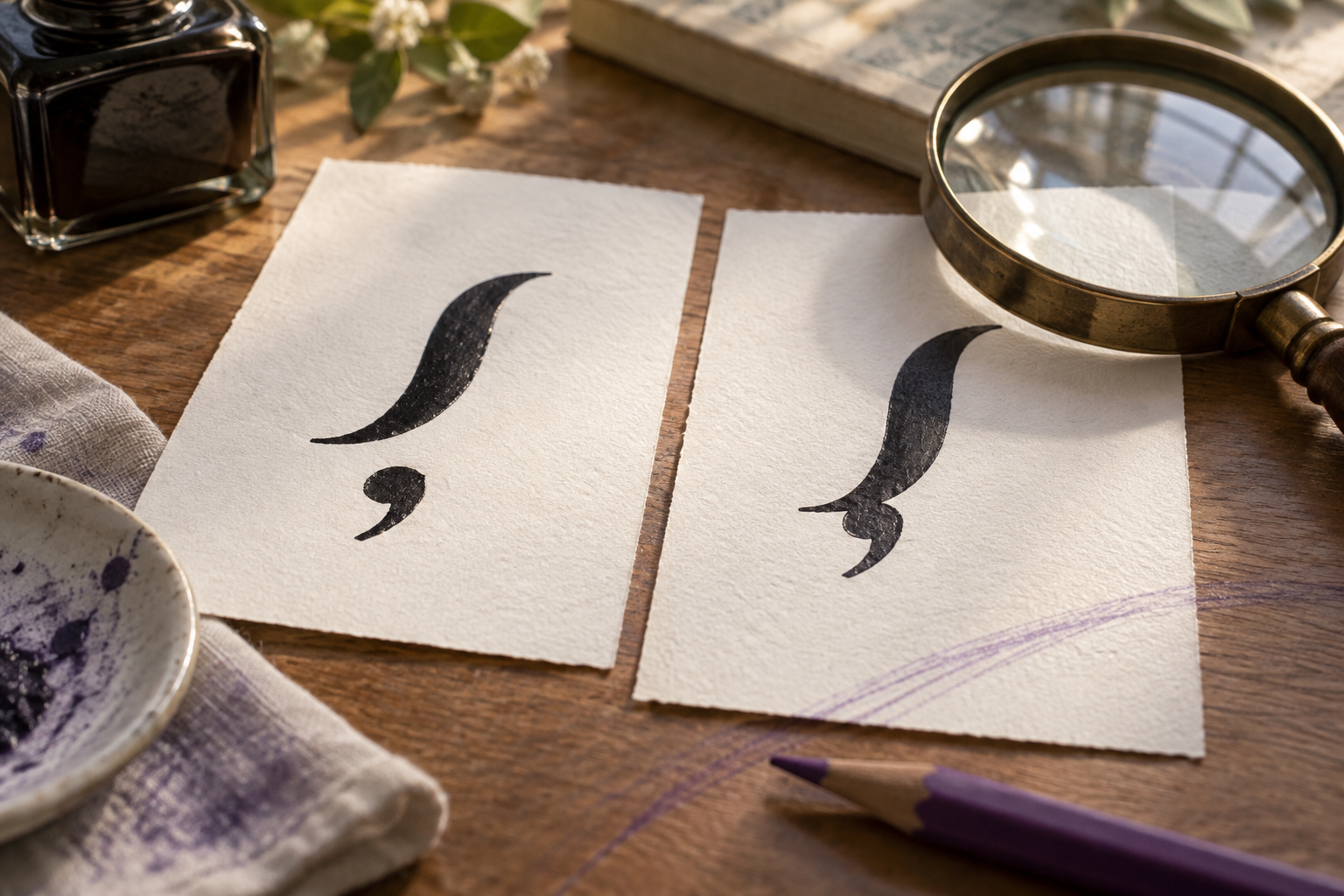
В румынском тексте буквы Ș/ș и Ț/ț несут собственные звуки и должны оставаться различимыми во всём наборе: в строчных и прописных формах, после копирования, при экспорте и на странице. Главная ловушка — похожие буквы с седилью: в старых данных они могли обозначать румынскую запятую снизу, хотя в Unicode у них отдельные коды и назначения. Проверяйте не только рисунок, но и сам текст.
Почему румынские знаки снизу легко перепутать
В румынском используются четыре буквы с запятой под основой: Ș, ș, Ț и ț. Их внешняя деталь располагается снизу, но это не просто декоративная вариация седили. Например, румынская строчная ș с запятой снизу отличается и от турецкой ş с седилью, и от обычной s. В наборе эти различия отвечают за правильное написание слов, поэтому шрифт должен показывать запятую явно, а текст — содержать подходящие символы.
Сходство кодов создаёт практическую проблему. В Unicode для румынских букв с запятой снизу предусмотрены U+0218 Ș, U+0219 ș, U+021A Ț и U+021B ț. У букв с седилью другие кодовые точки: U+015E Ş, U+015F ş, U+0162 Ţ и U+0163 ţ. В документации Unicode отдельно описана путаница, возникшая в старых наборах символов: один знак исторически использовали для нескольких визуально похожих форм. Для нового румынского текста следует различать запятую снизу и седиль, а при разборе старых данных учитывать возможную неоднозначность (Unicode Core Specification, раздел о запятой и седиле).
Начните с того, какие данные должен поддерживать шрифт
До рисования или проверки составьте короткий список ожидаемых текстов. Для обычных румынских фраз включите слова с ș и ț, заглавные буквы в заголовках или именах, а также прописные версии Ș и Ț. Если шрифт будет применяться вместе с турецким или в старых архивах, добавьте отдельно Ş/ş и Ţ/ţ. Это поможет не принять одну форму за другую и понять, где нужна языковая поддержка, а где — совместимость с полученными данными.
Полезно разделить задачу на три уровня:
- Символ есть в файле. Для каждого знака назначена отдельная кодовая точка и глиф; наборщик не подменяет его пустым прямоугольником или символом из другой гарнитуры.
- Форма соответствует языку. У румынских букв видна запятая снизу, а у символов с седилью — характерная форма седили. В маленьком размере отметка не должна сливаться с основой.
- Текст переживает рабочий маршрут. Символ не меняется при вставке, сохранении, экспорте макета, загрузке на сайт или повторном открытии файла.
Эти проверки отвечают на разные вопросы. Один красивый пример слова не доказывает, что в шрифте есть все четыре прописные и строчные формы. А наличие кодовой точки не гарантирует, что глиф хорошо нарисован, правильно привязан к метрикам и останется читаемым в конкретном кегле.
Составьте тестовый набор без случайных подмен
Возьмите по одному короткому слову или сочетанию для каждой нужной буквы. В тесте должны отдельно встречаться Ș, ș, Ț и ț, а рядом — обычные S/s и T/t. Если проверяется соседство с турецким, добавьте Ş/ş и Ţ/ţ. Не ограничивайтесь демонстрационной строкой ȘșȚț: она показывает наличие знаков, но почти ничего не говорит о ритме слова, интервалах или заметности нижних отметок.
Для проверки соседства удобно использовать три типа фрагментов: короткое слово с одной целевой буквой, слово с несколькими знаками и смешанный фрагмент, где рядом стоят S/T и румынские буквы. Сравните строчные и прописные версии в одной строке, затем повторите сравнение на более мелком кегле. Внизу отметки легко теряются у тесной строки или попадают в межстрочный интервал — это видно в контексте лучше, чем в таблице глифов.
Добавьте к образцу контрастную пару, например румынскую ș рядом с турецкой ş. Увеличьте фрагмент настолько, чтобы различить характер нижнего знака, а затем уменьшите до размера реального макета. Если две формы почти одинаковы, проверьте, не использует ли шрифт одну и ту же конструкцию или не подменился ли символ. Важно сохранять правильные кодовые точки: при ручном наборе легко вставить знакомый знак из другой раскладки и не заметить это по внешнему виду.
Проверьте составные и разложенные варианты
В текстовых данных румынская буква может быть представлена готовым символом либо базовой латинской буквой вместе с комбинируемым знаком снизу. Например, ș может прийти как U+0219 или как s плюс U+0326 COMBINING COMMA BELOW. Аналогично, ț может быть U+021B или t плюс U+0326. Это важно при копировании из разных редакторов, импорте архивов и работе с преобразованием текста.
Создайте тестовую строку с обоими представлениями каждой нужной буквы. При сравнении не ждите, что последовательности будут побайтно одинаковы: они имеют разное устройство, но могут обозначать канонически эквивалентный текст после нормализации. Unicode описывает NFC и NFD как формы нормализации; NFC обычно удобна для хранения общего текста, а NFD раскладывает некоторые знаки на основу и диакритический элемент (FAQ Unicode о нормализации, UAX #15).
Составной вариант проверяет глиф готовой буквы. Разложенный вариант проверяет сочетание базовой буквы и комбинируемой запятой: позиционирование отметки, высоту строки и поведение движка текста. Если готовый знак выглядит верно, а разложенный уходит слишком далеко вниз, касается соседней строки или оказывается сбоку, проблема может быть в метриках и обработке комбинируемого знака. Отдельно осмотрите результат после копирования в целевой редактор: его движок, резервные шрифты и правила нормализации могут изменить отображение.
Для румынского текста недостаточно нарисовать небольшую отметку под S и T: нужно различать запятую снизу и седиль, проверить четыре кодовые точки и убедиться, что готовые и разложенные варианты читаются в рабочем макете. Сохраните короткий тестовый набор вместе с проектом и повторяйте его после каждой версии шрифта. Это занимает мало времени и помогает обнаружить замену, обрезку или неверную форму до публикации.